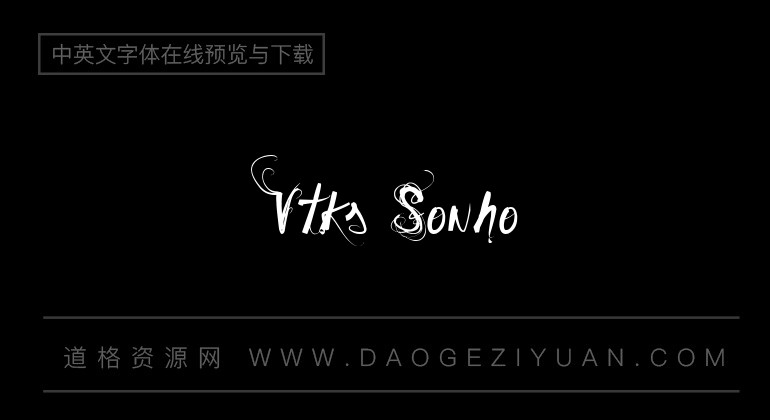
? Vtks Sonho 字体是一款现代复古风格的手写字体,它具有一种温暖的感觉。它的笔画圆润而不失细节,每个字母都有一种温暖的感觉,就像有人在轻轻地抚摸着你的心。它的字体比较粗糙,但又具有一定的灵活性,能够更好地表达出你想要的感受。Vtks Sonho 字体适用于卡片、海报、广告等设计,能够为你的作品增添一份温暖的气息。内容介绍
Vtks Sonho是一款非常不错的手写艺术字体,具有很好的视觉感,适合于文化类的宣传设计、商业类品牌的广告和产品包装设计以及个性化文字排版等较多场景。